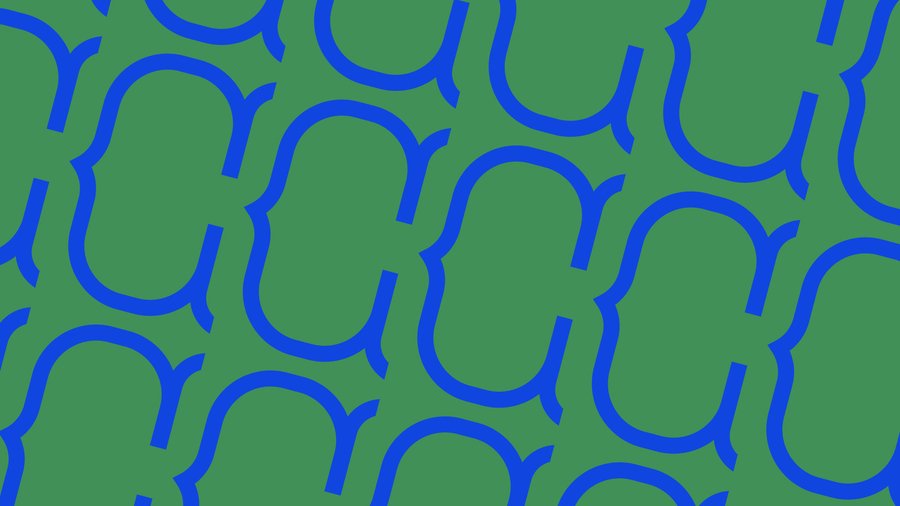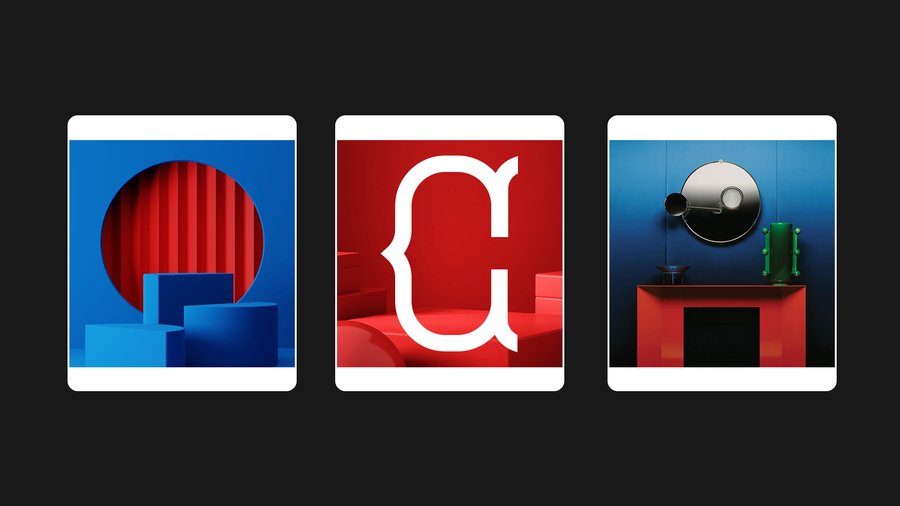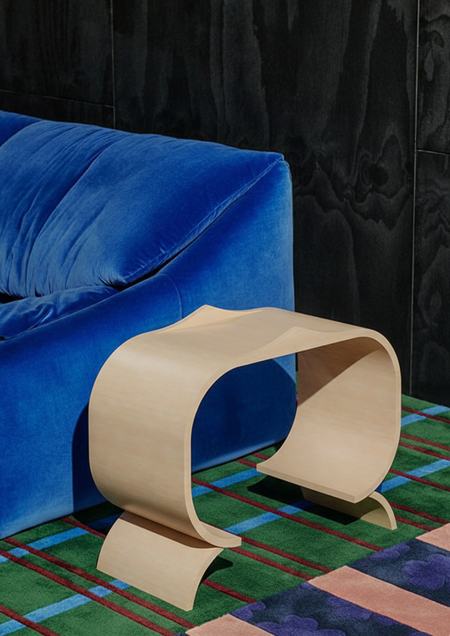
Столик по мотивам Circus Font
Circus — модульный шрифт, вдохновлённый цирковой эстетикой и основанный на системе округлых форм. Его пластика и логика построения были переосмыслены в формате модульного столика, повторяющего характер начертания на уровне формы и структуры. В основе проекта лежит идея модульности и трансформации графического элемента в предмет среды.